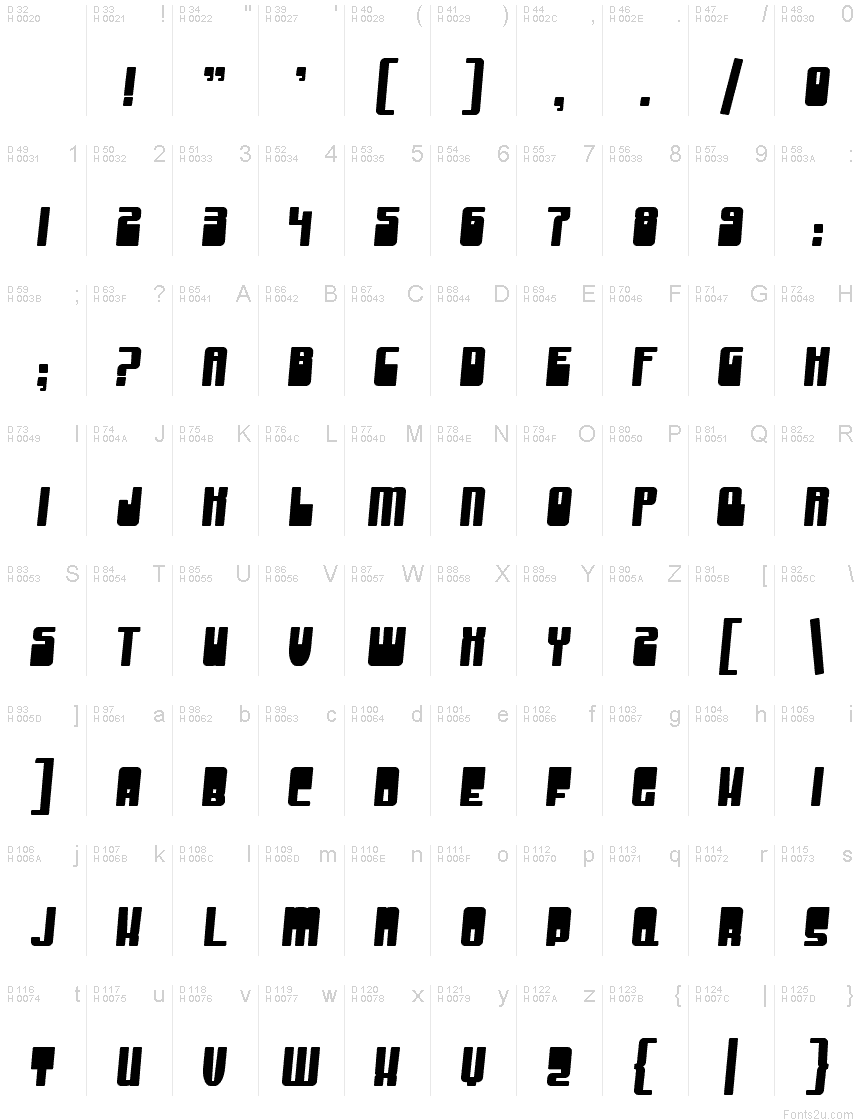
Groove Machine Bold od Shywedge to darmowy, utrzymany w stylistyce groovy krój pisma, który uderza z siłą basowego dropu. Ciężkie, pochylone litery ruszają do przodu dzięki grubym, blokowym kształtom i napiętemu rytmowi, który sprawia wrażenie wyjętego prosto z rave'owego plakatu lat 90. Masywne sylwetki tworzą wizualną ścianę, która natychmiast przykuwa uwagę, a subtelne krzywizny sprawiają, że całość jest zabawna, a nie ostra.
Używając Groove Machine Bold, Twoje projekty błyskawicznie wchodzą w „tryb imprezowy” – ten darmowy font świetnie sprawdza się na plakatach klubowych, logotypach DJ-ów, retro okładkach albumów, identyfikacjach wizualnych eventów, miniaturach na YouTube oraz odważnych grafikach na gadżety. Użyj go w dużym rozmiarze dla maksymalnego efektu, a w mniejszych zestawieniach połącz z czystym, neutralnym krojem bezszeryfowym, aby zachować czytelność detali, podczas gdy nagłówek będzie grał główną rolę.